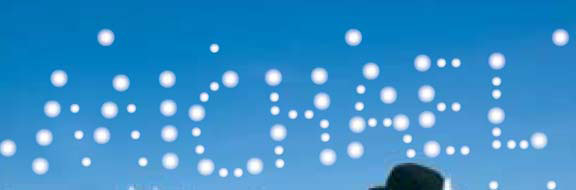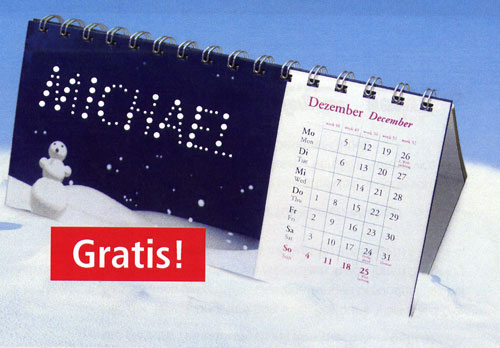
FontShop beschert Postbank eine WeihnachtsschriftAuch das ein Fall für die Abteilung Corporate Font: Das
Erstellen einer Spaßschrift für eine Weihnachts-Werbeaktion der
Postbank AG. Mehreren Zehntausend Kunden sollte die Bestellung einer
Postbank-Visa-Card mit einem ganz persönlichen Geschenk versüßt
werden, nämlich einem Tischkalender mit dem eigenen Namen –
fotografisch aufbereitet – auf jedem Blatt. Das Dezemberblatt
beispielsweise zeigt den Vornamen aus Schneeballspuren. Weiterlesen ...
Im November letzten Jahres flatterte uns dieses PDF ins Haus, quasi das
Briefing für eine außergewöhnliche
Schrift:
![]() Gefordert war eine Schneeball- oder Schneeflocken-Schrift aus unterschiedlich großen Punkten. Sie sollte im Rahmen eines serialisierten Mailings zum Einsatz kommen, das einen mit Vornamen beschrifteten Jahreskalender zum Thema hat. Da der Font für eine Kalenderfläche mit eingeschränktem Platz geplant war, musste die Schrift möglichst schmal laufen und trotzdem gut lesbar bleiben. Da müssen sich ähnliche Buchstaben visuell stärker abgrenzen, was Corporate Font durch das Setzen unterschiedlicher »Punktgrößen« löste. Da mit dieser Schrift lediglich Vornamen gesetzt werden, enthielt die Schrift lediglich die Versalien, Aktenzverknüpfungen (Windows Latin 1) und die Horizontalstriche. Ausgeliefert wurde der Font termingerecht im PC-TrueType-Format. ![]() Aus dem im Dezember von der Postbank versendeten Mailing: Abbildung eines serialisierten Jahreskalenders Herausgegeben: Di - Januar 10, 2006 at 10:00 vorm. | |